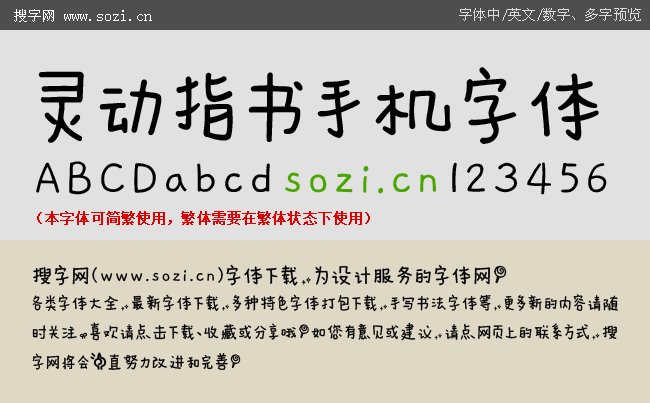
靈動(dòng)指書手機(jī)字體
搜字網(wǎng)給大家提供一款卡通手寫風(fēng)格的手機(jī)中文字體下載。名字叫靈動(dòng)指書手機(jī)字體,這款手機(jī)字體是仿照兒童手寫風(fēng)格的卡通手寫字體,結(jié)構(gòu)帶有POP字體風(fēng)格,特別適合喜歡卡通的朋友在手機(jī)上安裝使用。